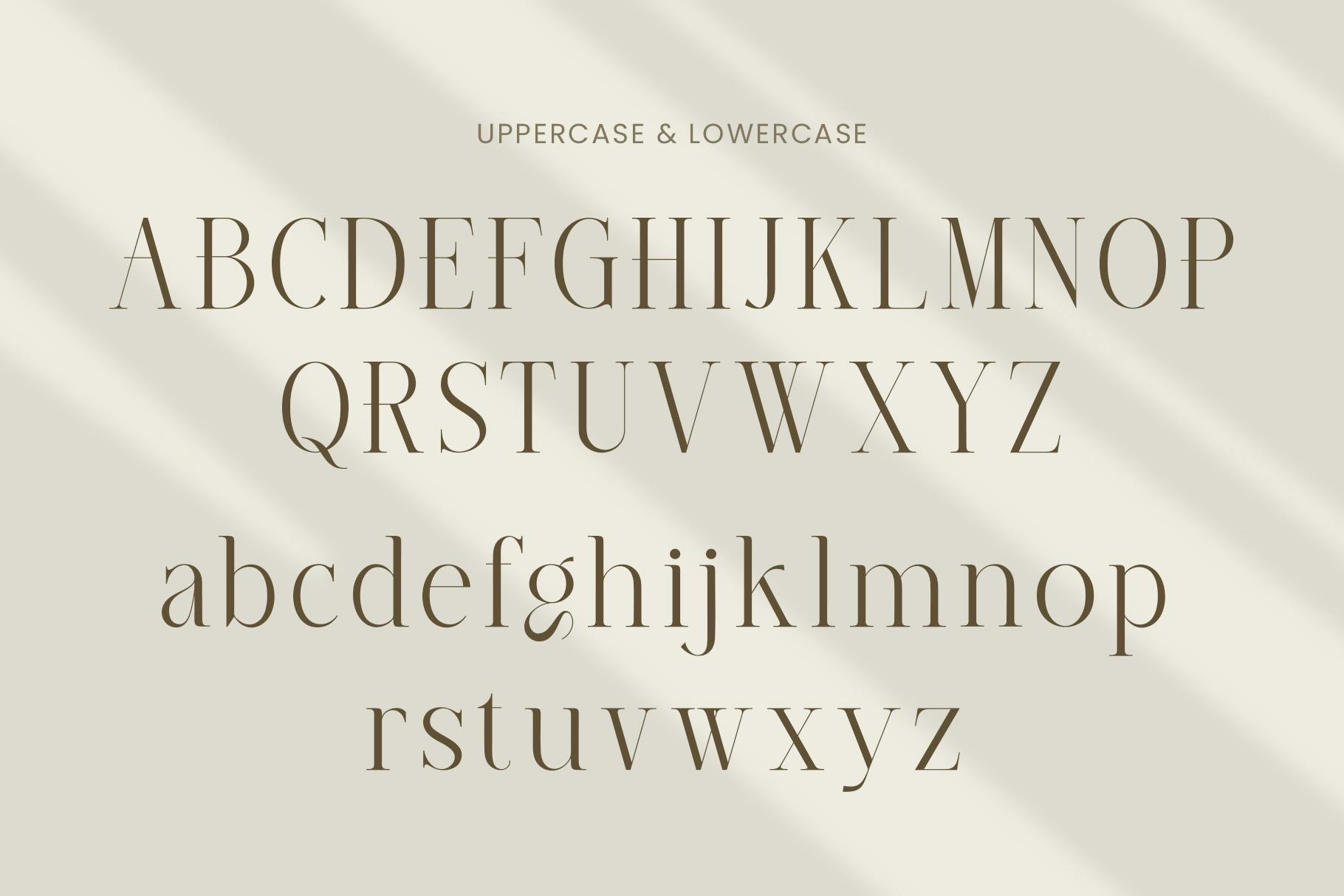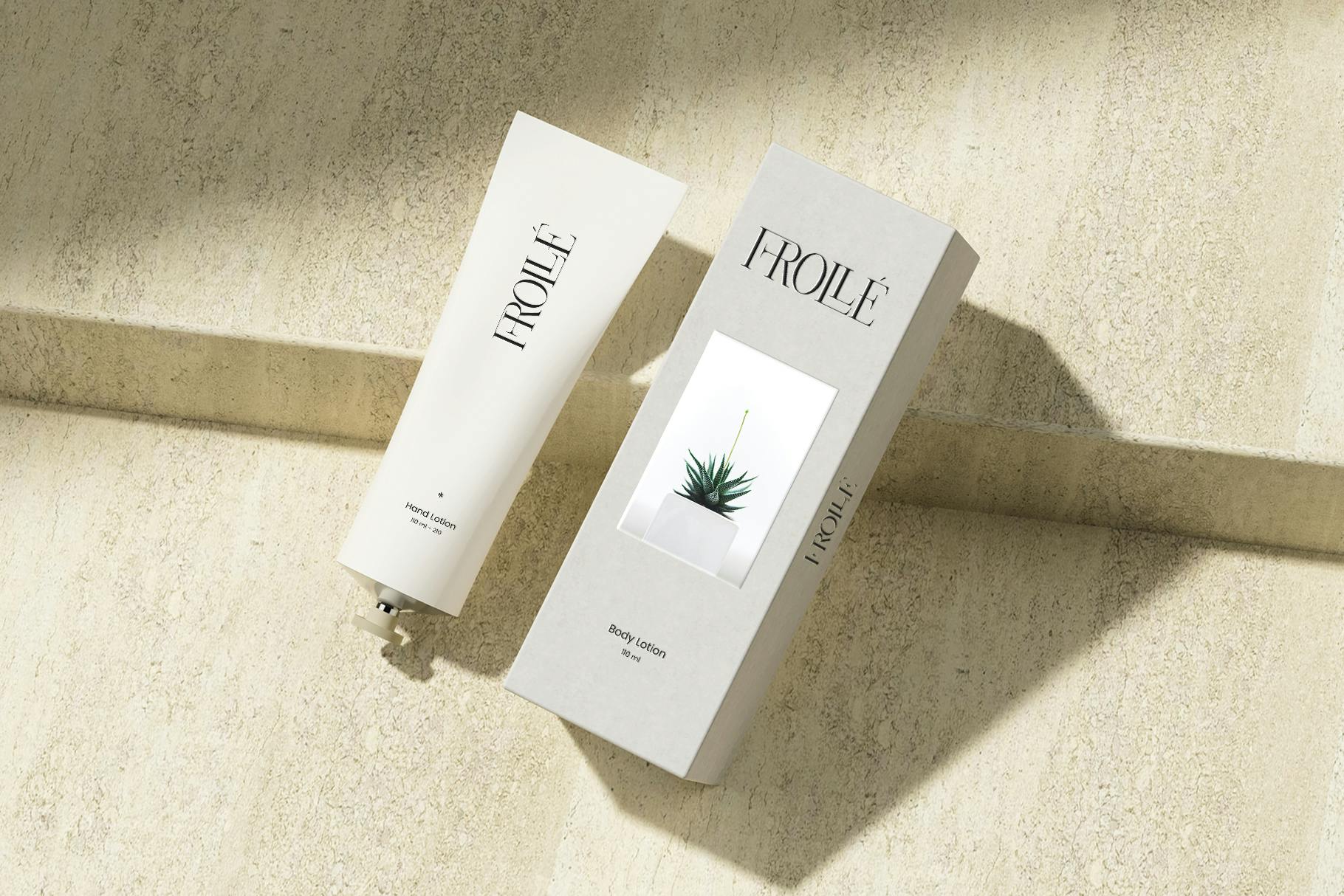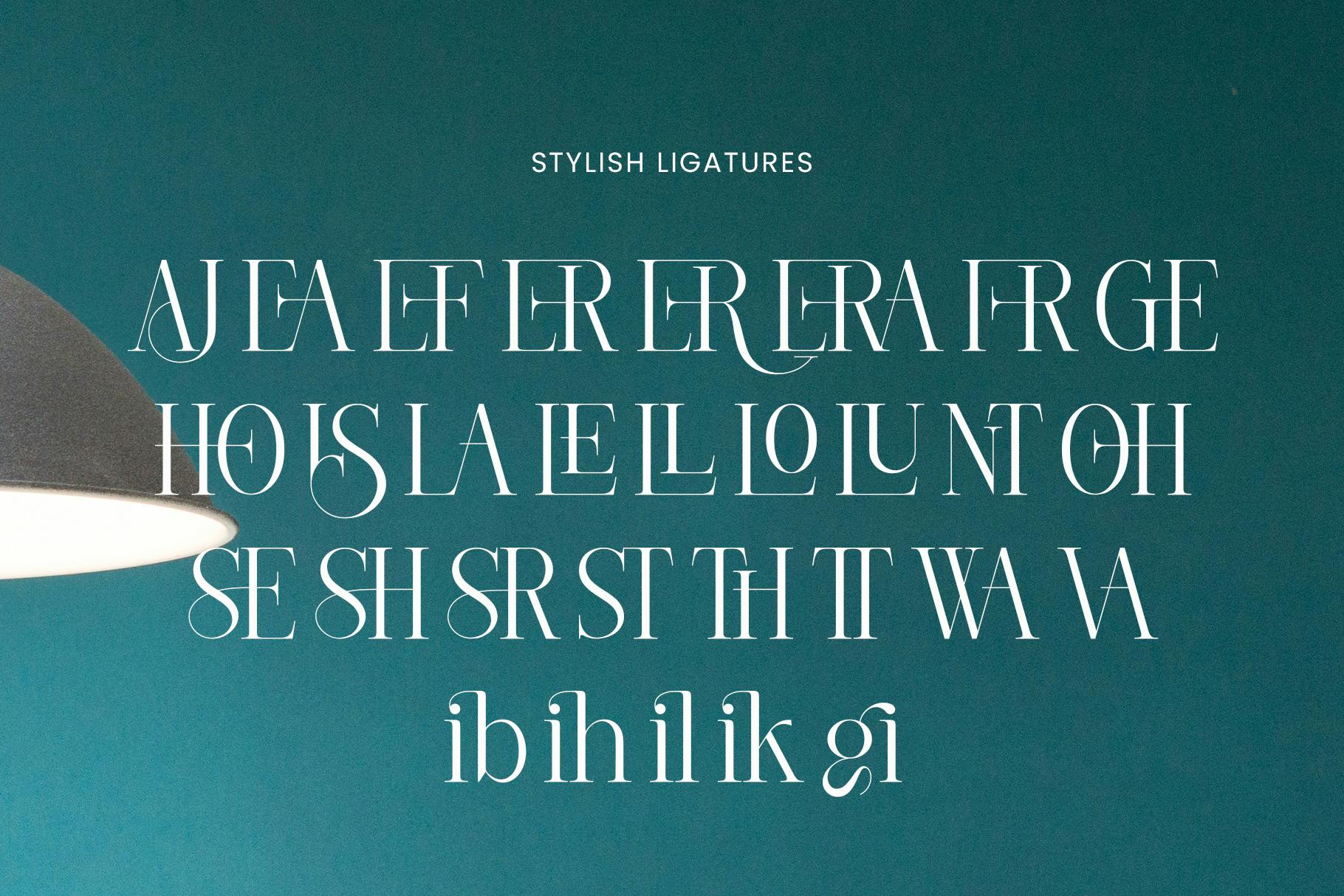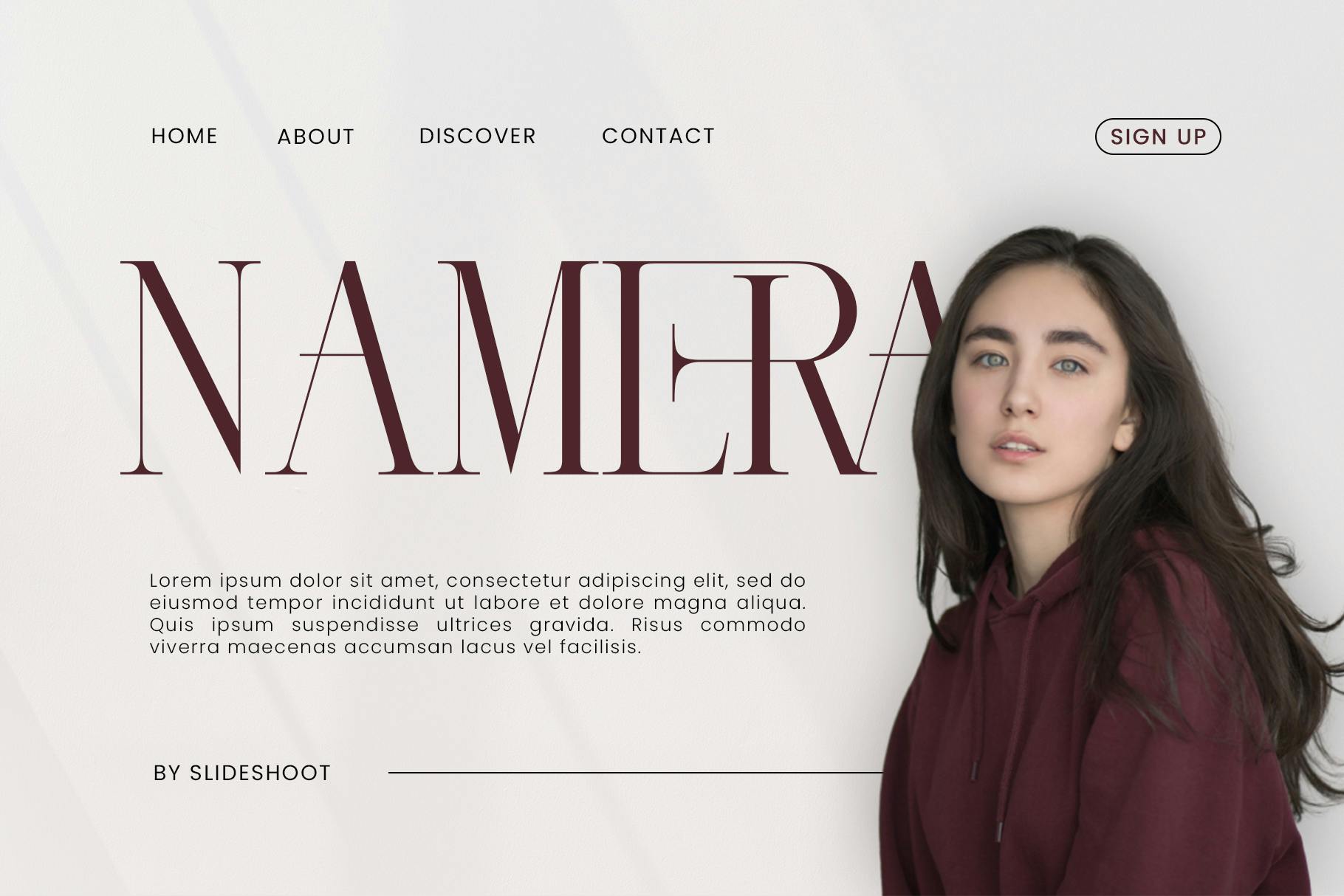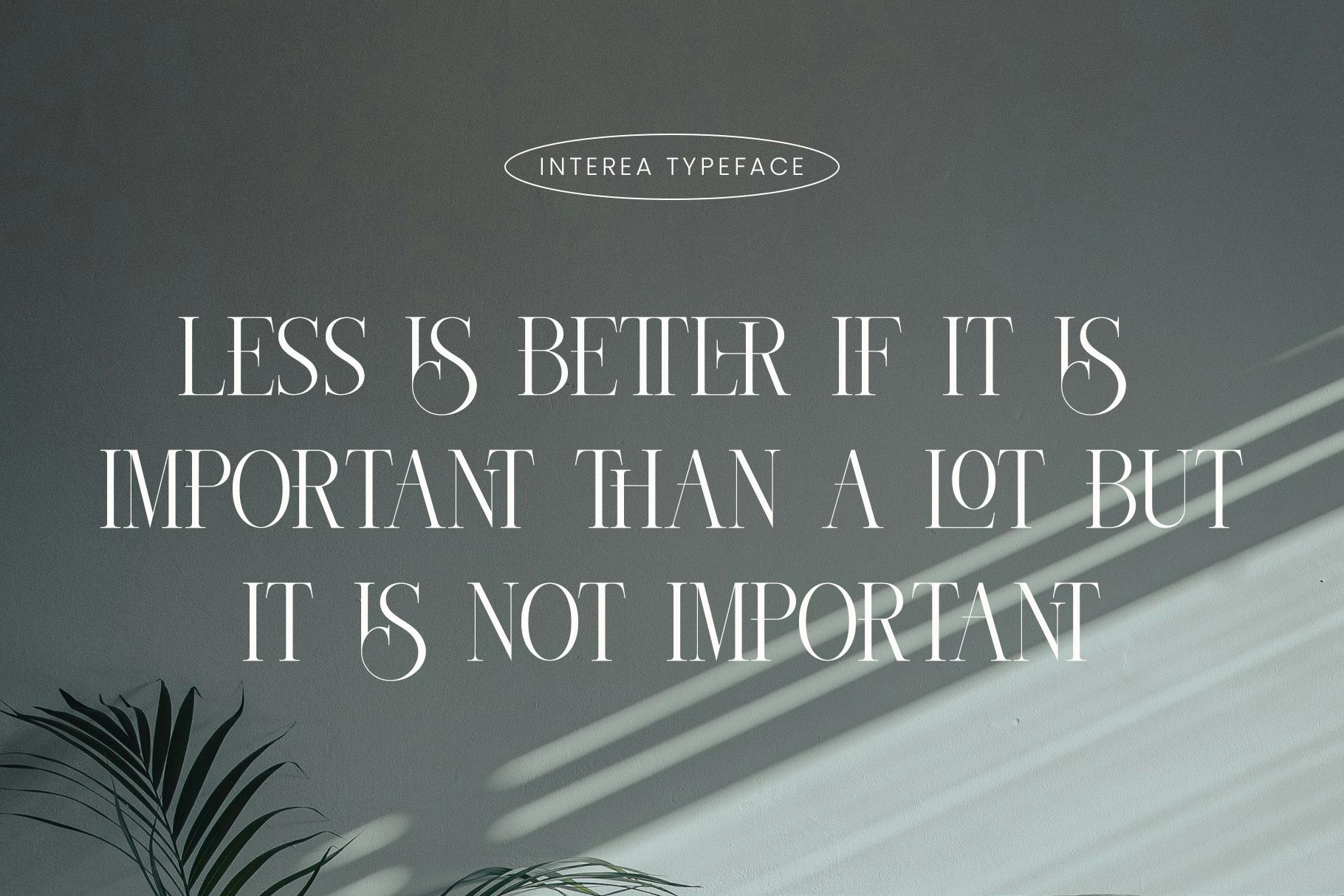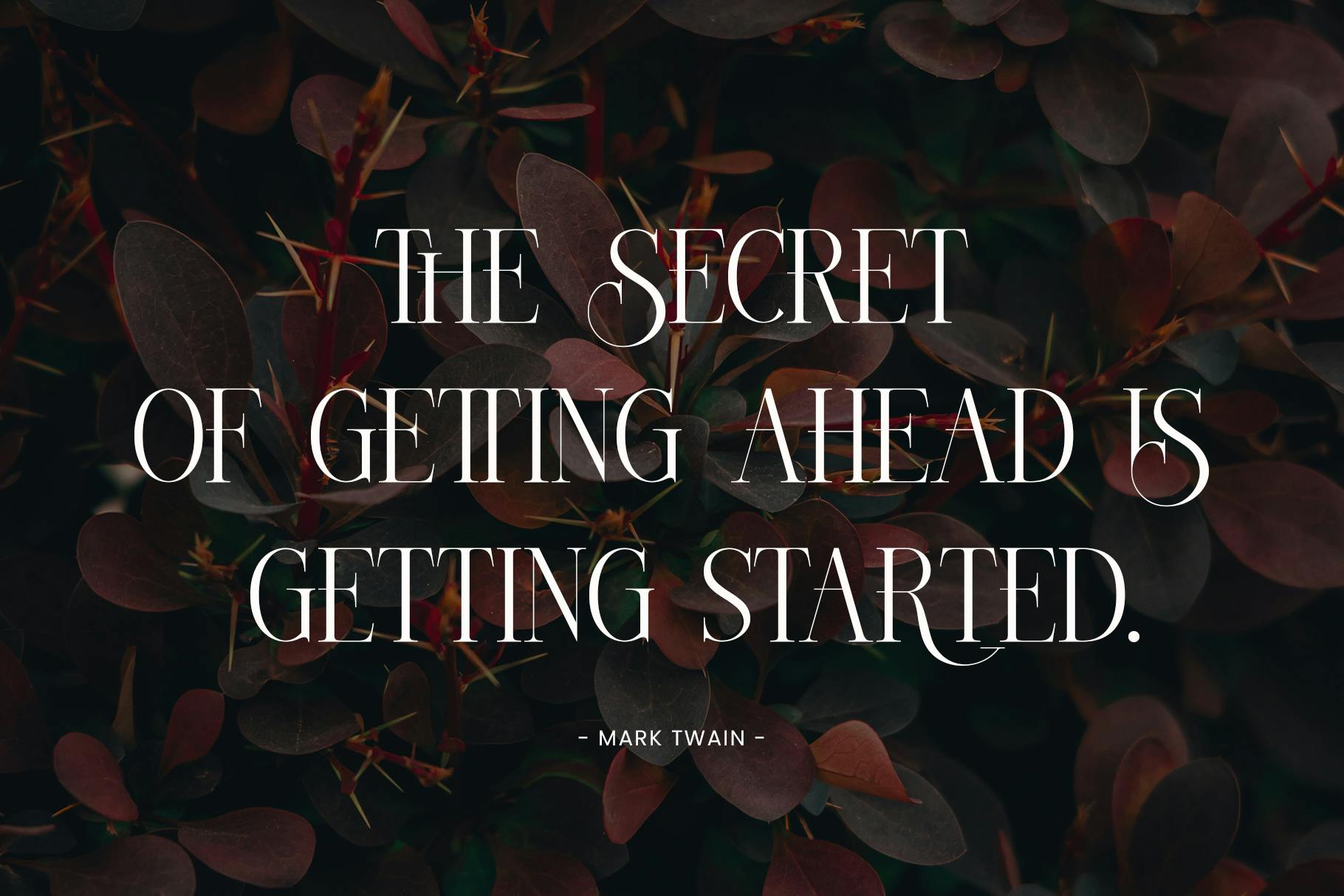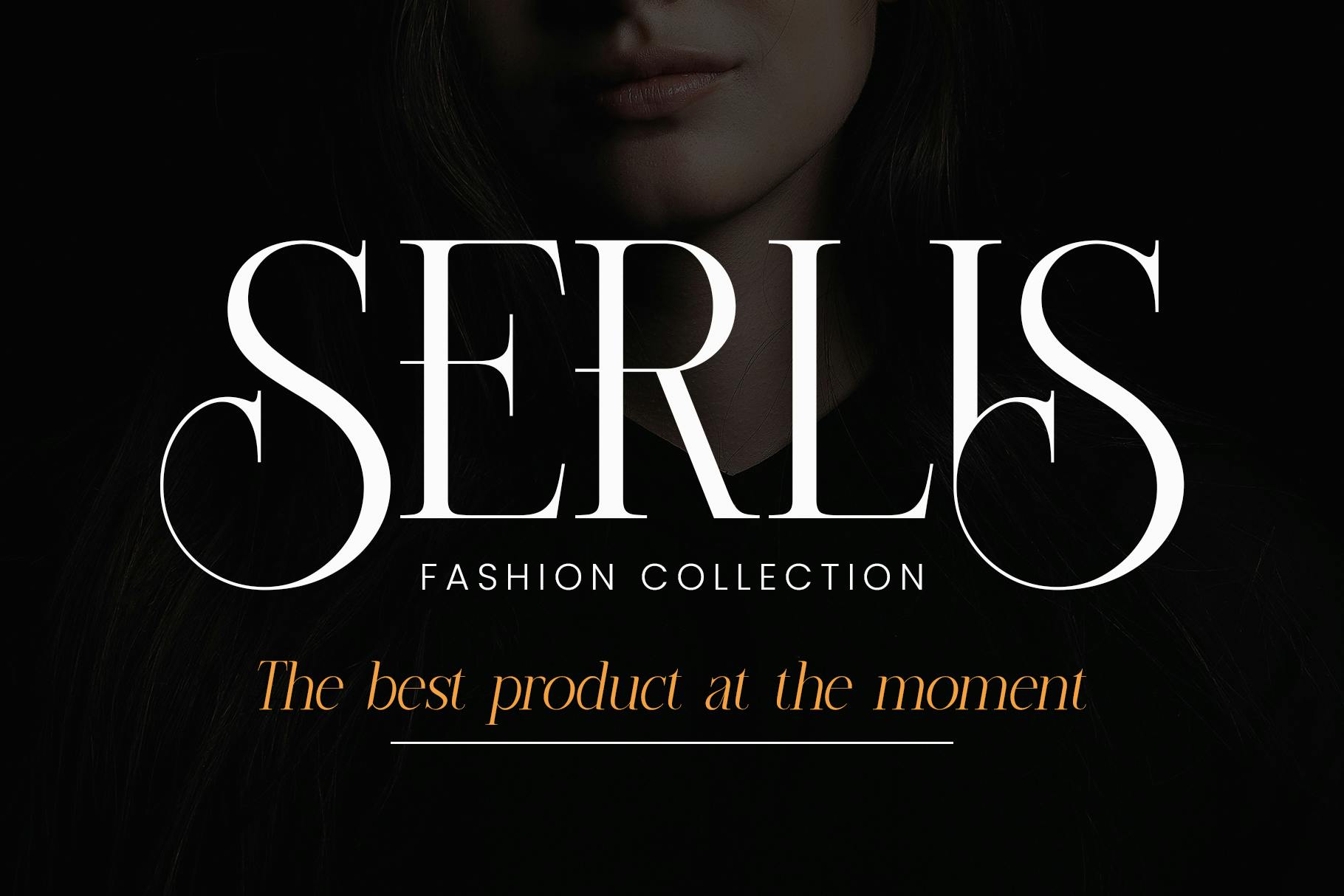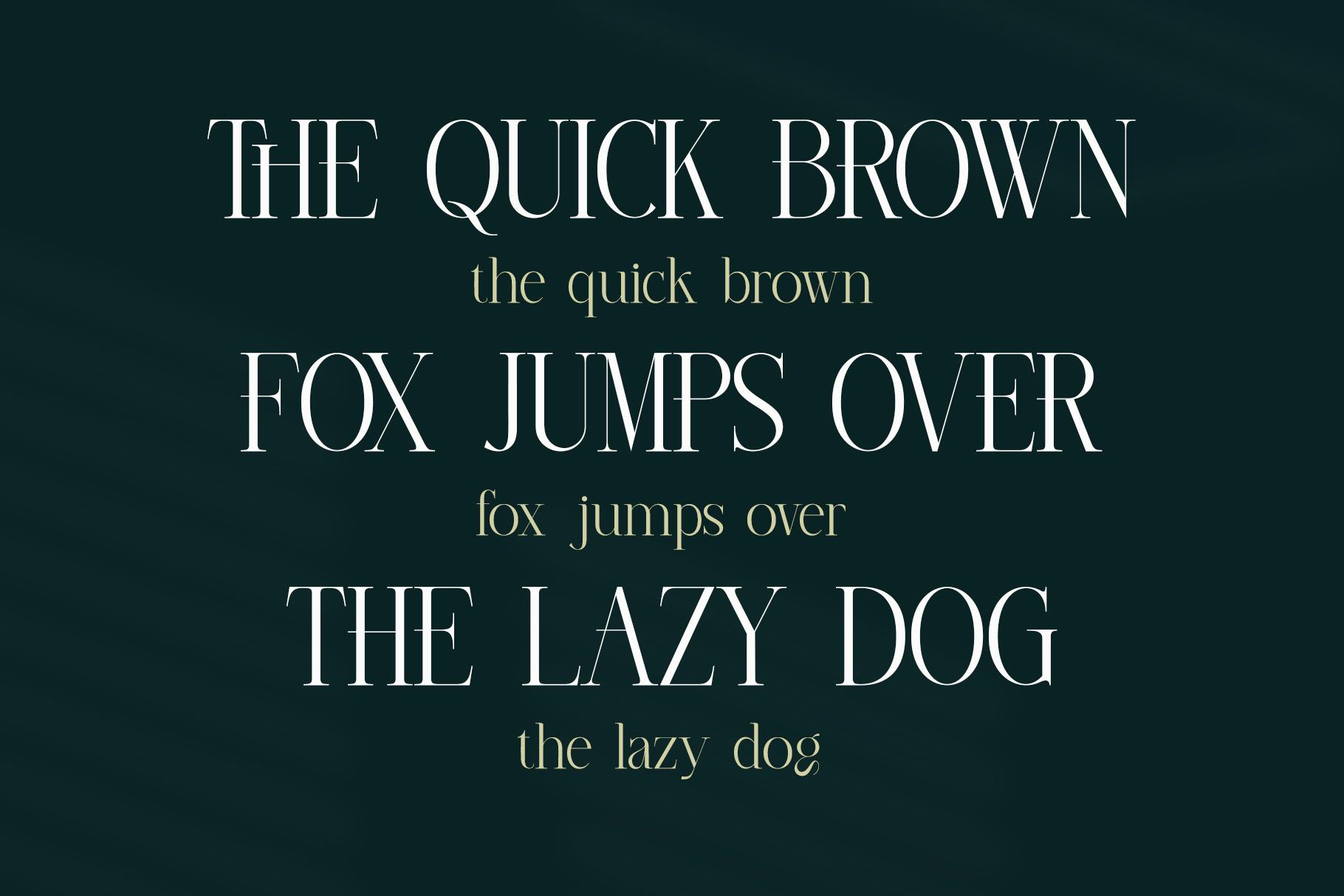
دانلود فونت لوکس Interea Serif با طراحی شیک
Interea A Luxury Serif Font
فونت Interea Serif با طراحی زیبا و شیک، انتخابی ایده‌آل برای پروژه‌های شما.
فونت Interea Serif یک فونت سریف متعادل، نرم، شیک و با ظاهری زیبا است. این فونت با شخصیت منحصر به فرد خود، به‌طور کامل با طراحی کارت‌های دعوت، لوگوهای شرکتی، عناوین فیلم‌ها، کارت‌های ویزیت، عناوین کتاب‌ها، نام برندها و طراحی‌های مختلف دیگر هماهنگ می‌شود. Interea Serif یک فونت سریف ظریف است که حس پیچیدگی و elegance را منتقل می‌کند. تغییرات و لیگچرهای شیک این فونت، آن را به شریک ایده‌آل برای هر پروژه‌ای تبدیل می‌کند.
ویژگی‌ها:
• لیگچر
• حروف بزرگ و کوچک
• شماره‌گذاری و علائم نگارشی